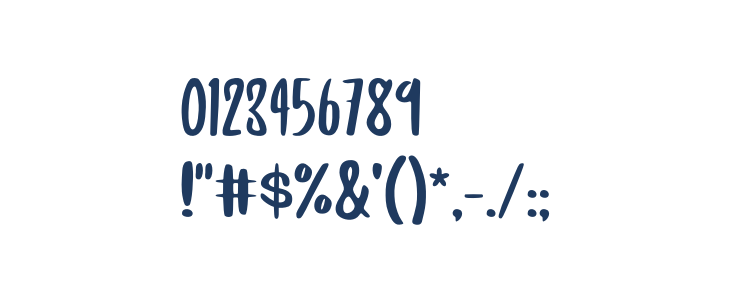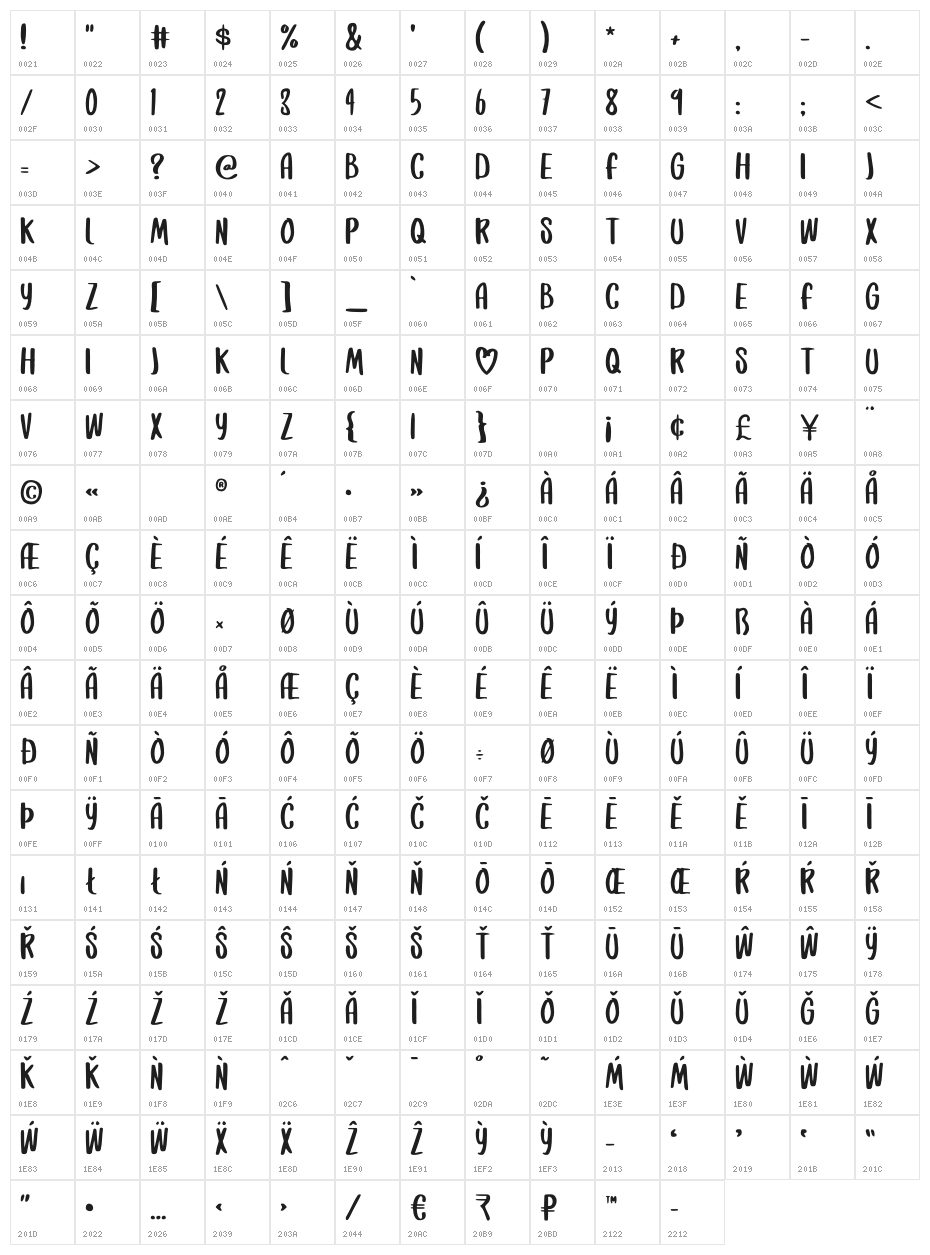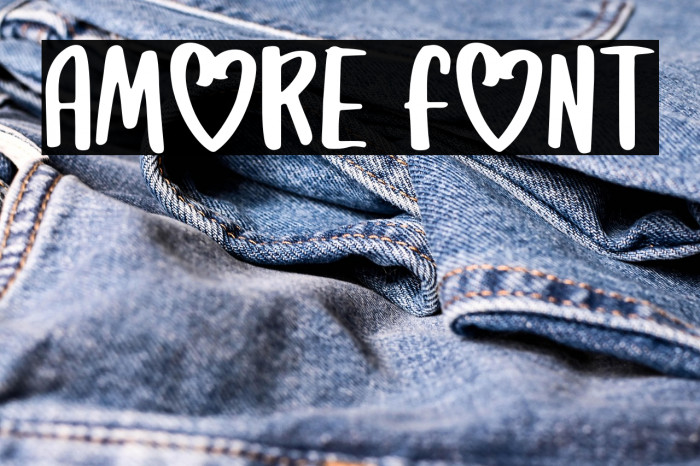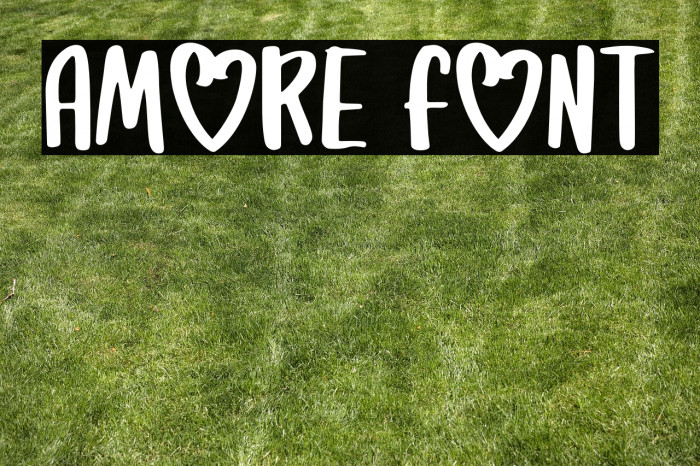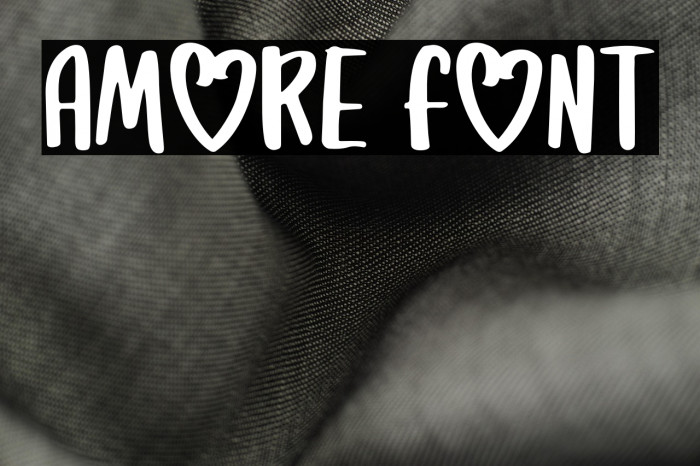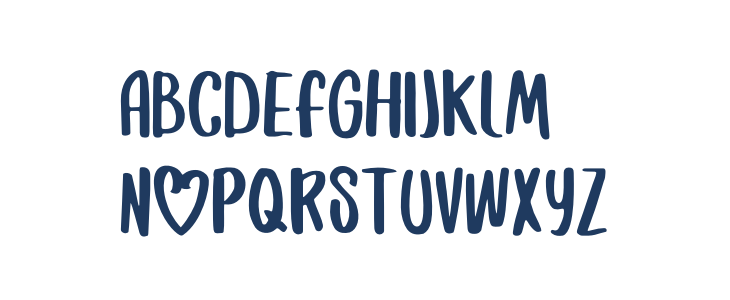
Amore Font
| Caso d'uso | Headlines, Logos, Invitations |
| Progetti proposti | Ideal for children's books, greeting cards, playful branding, and casual invitations. |